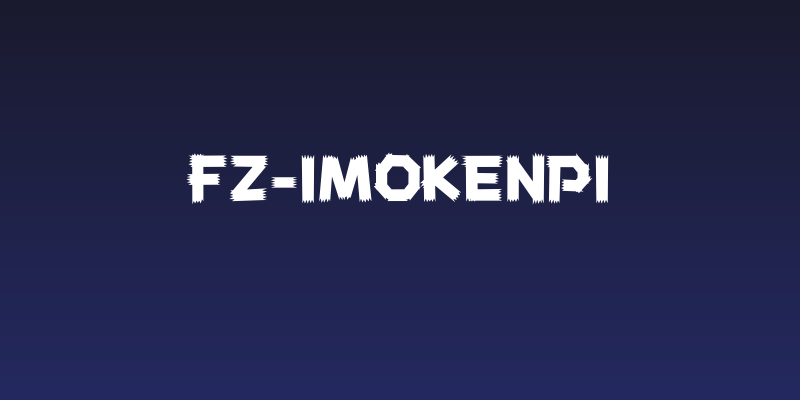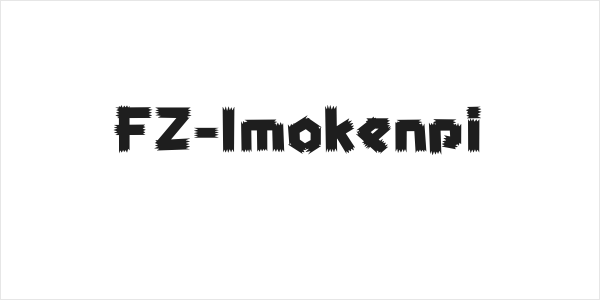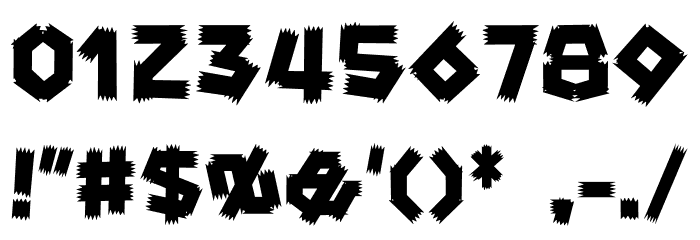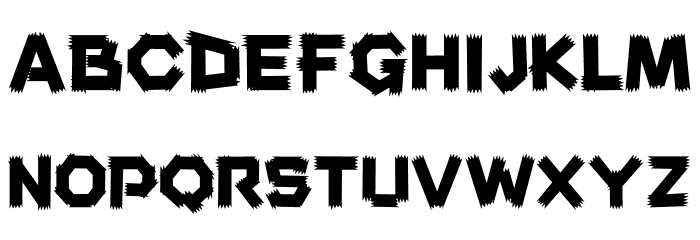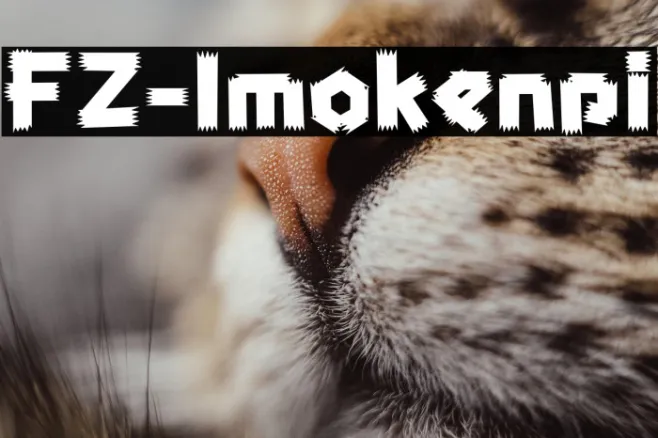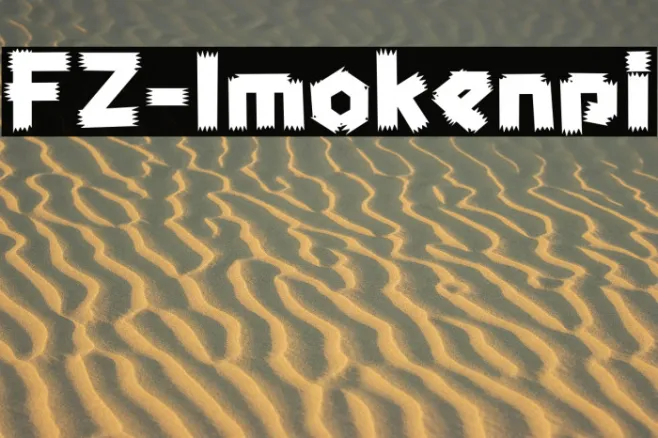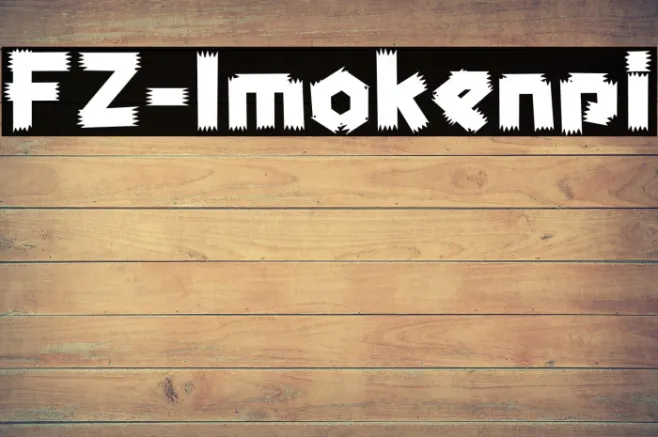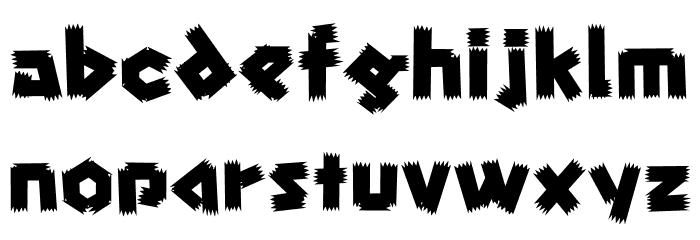
FZ-Imokenpi Font
| Vorgeschlagene Projekte | Ideal for music album covers, event posters, video game titles, or any project needing a bold, edgy aesthetic. |